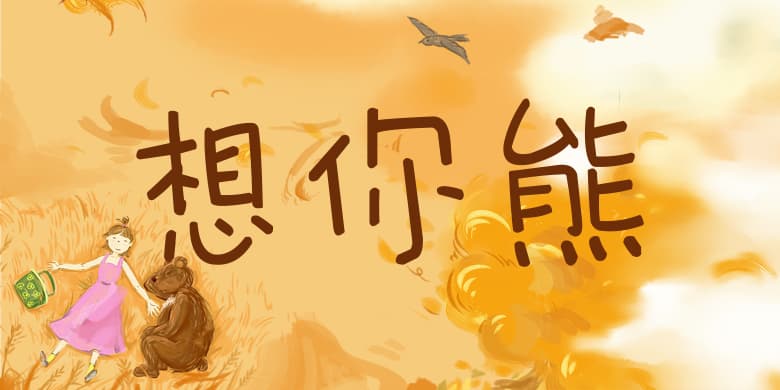
方正手迹-想你熊
品牌:方正手迹设计师:刘殿儒发行时间:2019字库编码:大陆简体(GB2312-80)分类:创意书写字体属性:精品字
想你熊是一个IP字体,该字字形敦厚可爱,重心看似不稳,有一定的倾斜角度,实则恰好能展现小熊活泼可爱的动态形象。适用于少儿类书刊,及现代诗歌、短文的排版以及文化、商业类品牌的广告语设计。